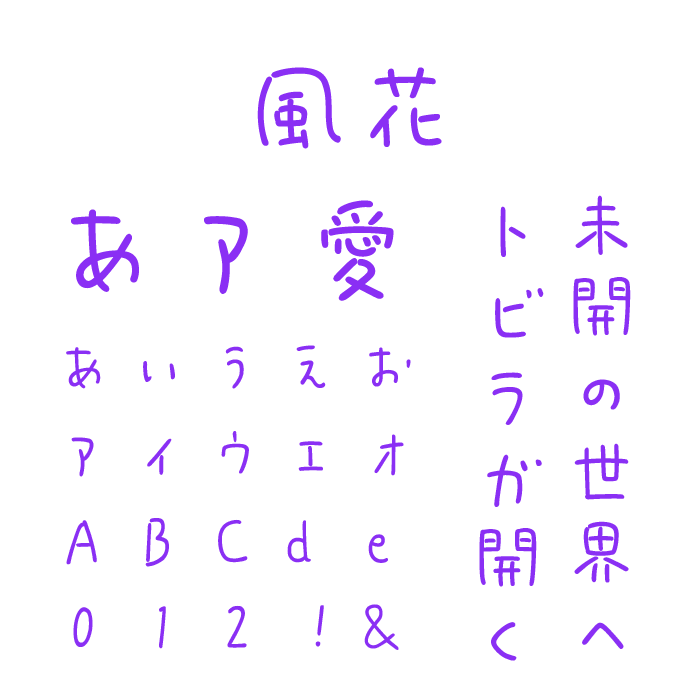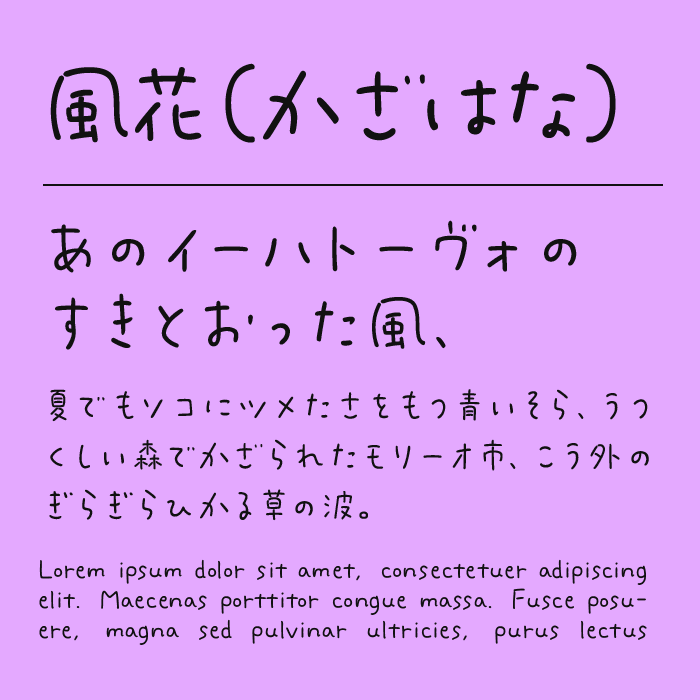
風花(Kazahana)フォントは、細くしなやかなストロークが印象的な手書き風フォントです。
やや縦長のフォルムと、ところどころに揺らぎのある線が、風に舞う花びらのような繊細さを演出しています。洗練された雰囲気の中に、素朴な温かみも感じられます。
力の抜けた柔らかな書きぶりは、日記や手紙、詩的なコンテンツとの相性が抜群です。感情を静かに伝えるシーンに向いており、大人っぽくも親しみを持てる印象を与えるフォントです。雑貨やライフスタイルメディアにもよく馴染みます。